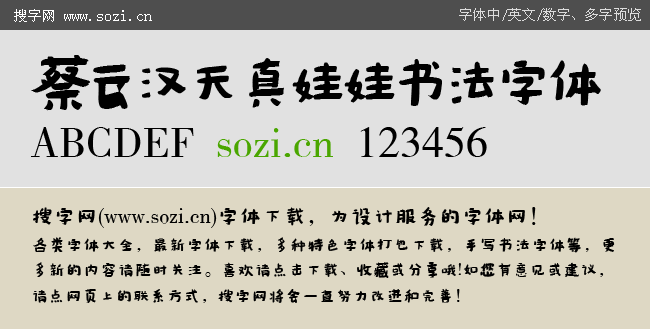
蔡云漢天真娃娃書法字體
搜字網(wǎng)提供一款卡通風(fēng)格的書法字體下載,蔡云漢天真娃娃書法字體是一款融合了現(xiàn)代卡通書體風(fēng)格的中文漢字,在具有卡通幾格的同時(shí),又兼具書法韻味,適合平面設(shè)計(jì)、廣告創(chuàng)意、兒童畫報(bào)等廣告設(shè)計(jì)。